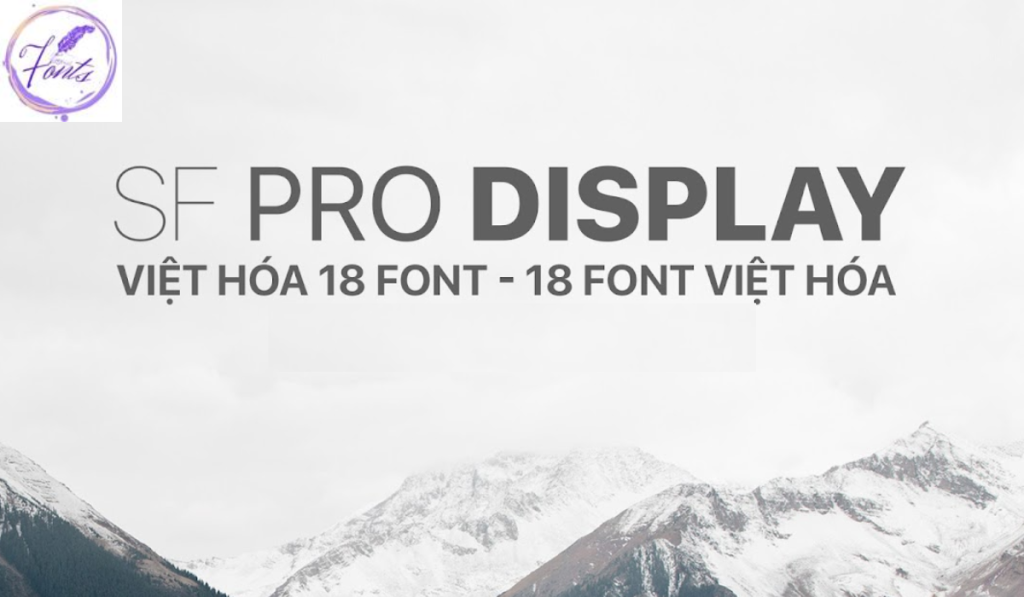
Font New SF Pro Display Việt hóa
Tác giả: Apple Inc.
Ngày phát hành: 2015
Ngôn ngữ: Tiếng Việt, Tiếng Anh, và nhiều ngôn ngữ khác
Bộ Font: SF Pro
Phân loại: cá tính, độc đáo, hiện đại
Kiểu chữ: sans serif
Độ dày: Ultralight, Thin, Light, Regular, Medium, Semibold, Bold, Heavy, Black
Font New SF Pro Display Việt hóa thuộc bộ font SFU một trong những font chữ được thiết kế đặc biệt để mang đến vẻ đẹp hiện đại và chuyên nghiệp cho các tác phẩm thiết kế. Font này là phiên bản Việt hóa của font San Francisco, được Apple thiết kế năm 2015 và sử dụng rộng rãi trong hệ điều hành và các sản phẩm của mình. Với sự cân bằng tuyệt vời giữa thiết kế đơn giản và tính năng đọc dễ dàng, font new sf pro display là lựa chọn lý tưởng cho cả in ấn và hiển thị kỹ thuật số.
Đánh giá font new sf pro display việt hóa
Font new sf pro display việt hóa được đánh giá cao bởi các nhà thiết kế đồ họa và các chuyên gia truyền thông. Với nhiều trọng lượng và kiểu chữ khác nhau từ Light đến Black, font này cho phép sự linh hoạt trong thiết kế, từ tiêu đề đậm nhấn mạnh đến nội dung cơ bản dễ đọc. Sự hỗ trợ đầy đủ các ký tự tiếng Việt cũng giúp người sử dụng dễ dàng ứng dụng font này vào các dự án đa ngôn ngữ, mở rộng khả năng sáng tạo.